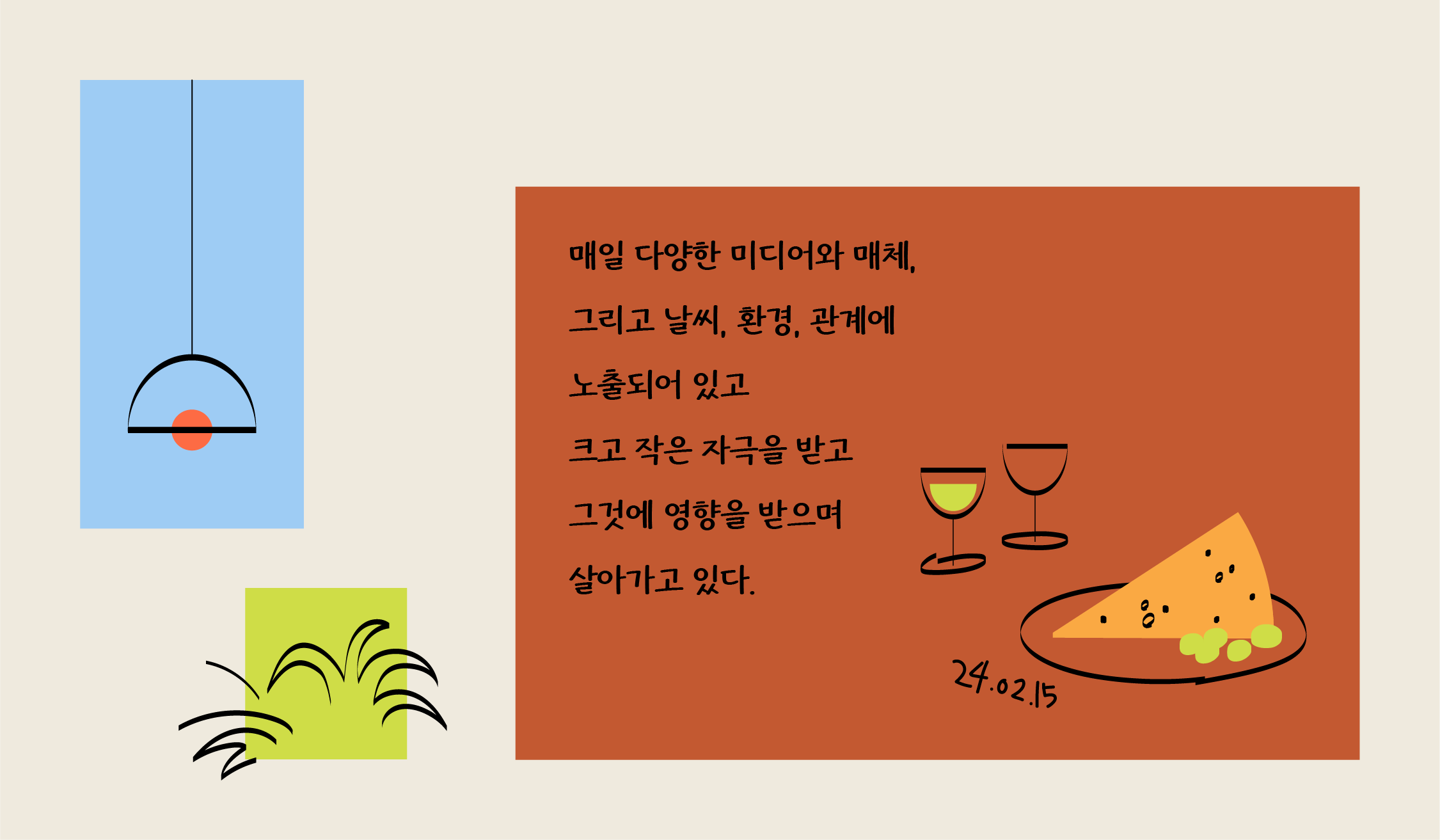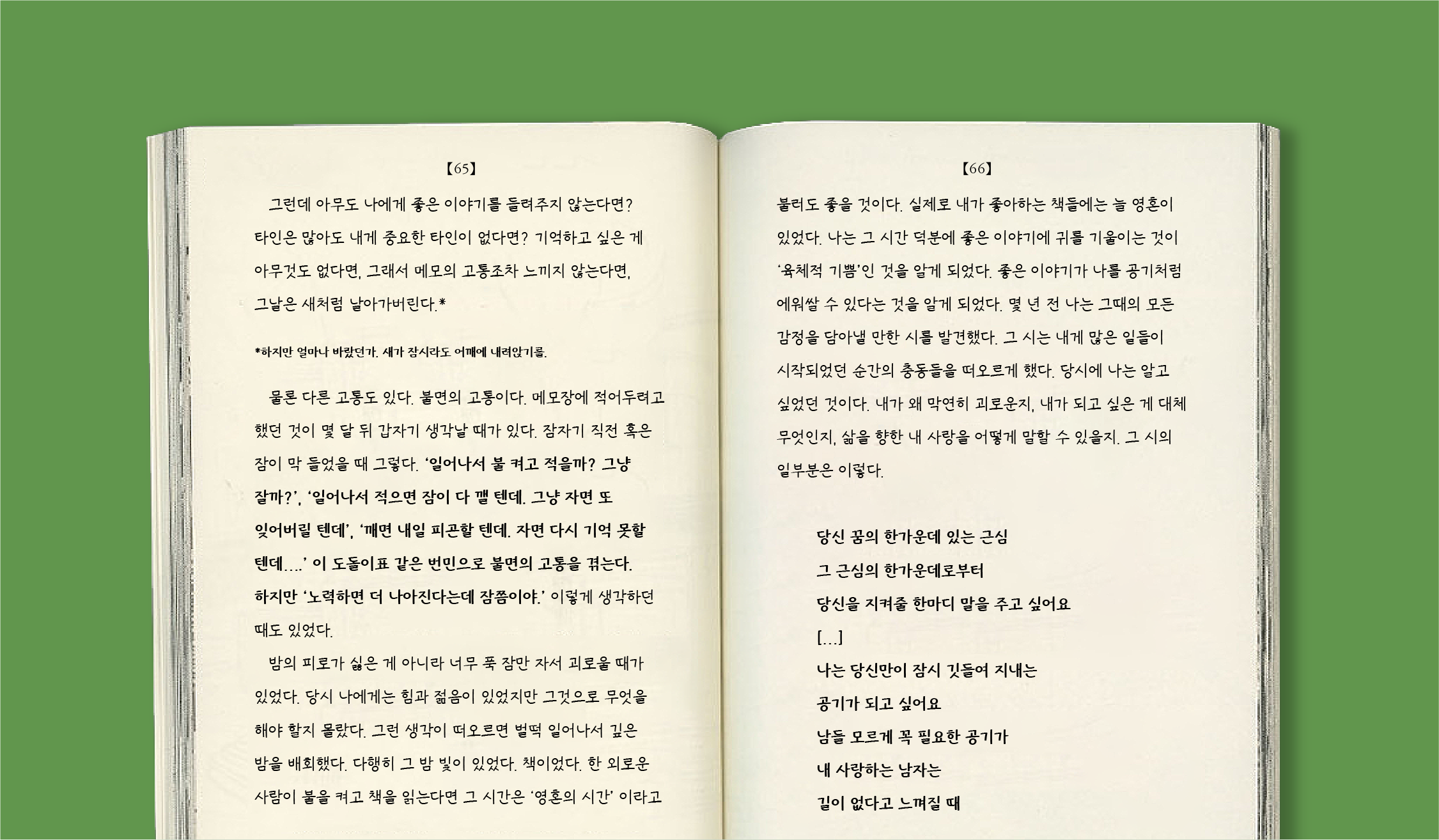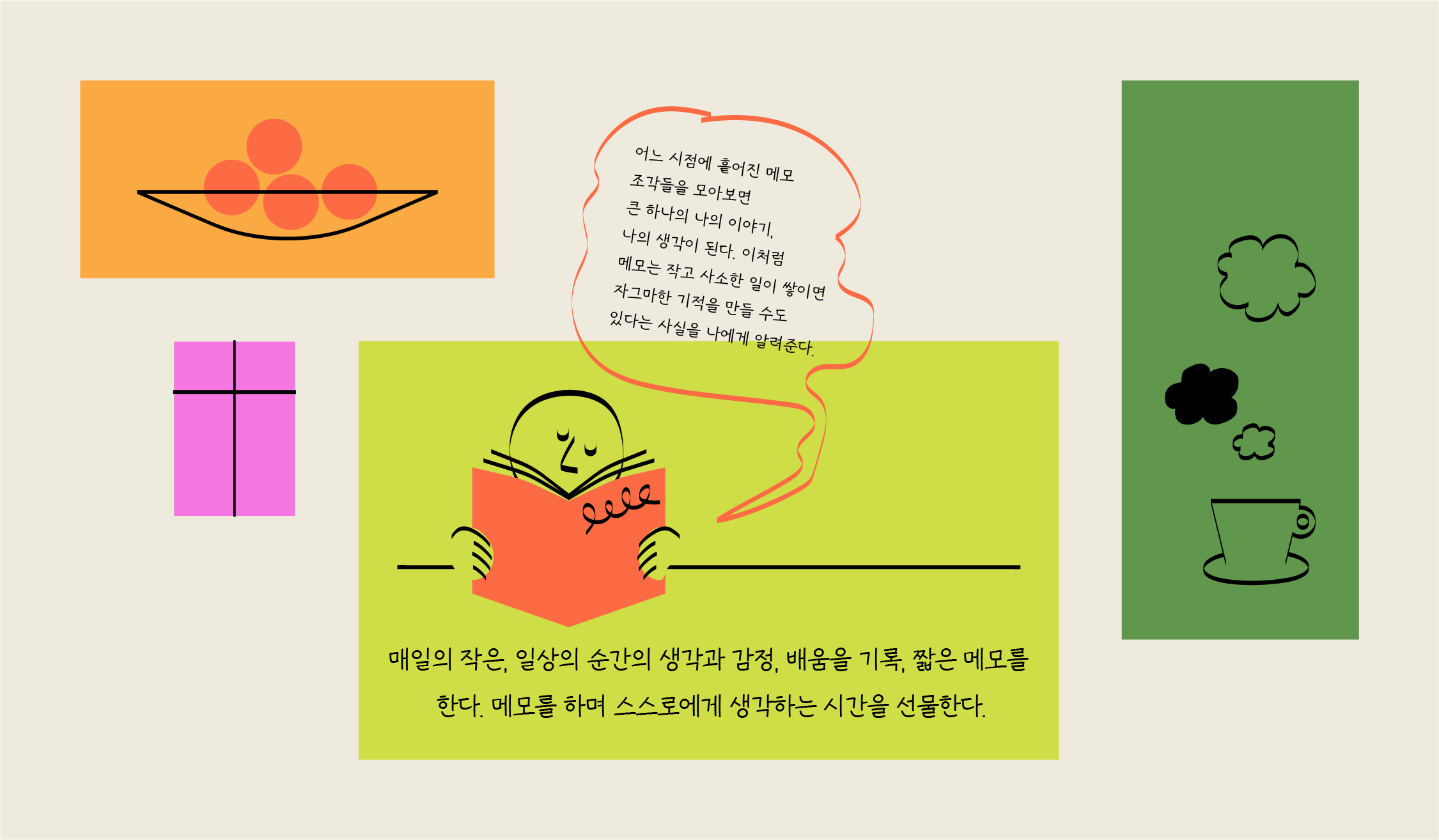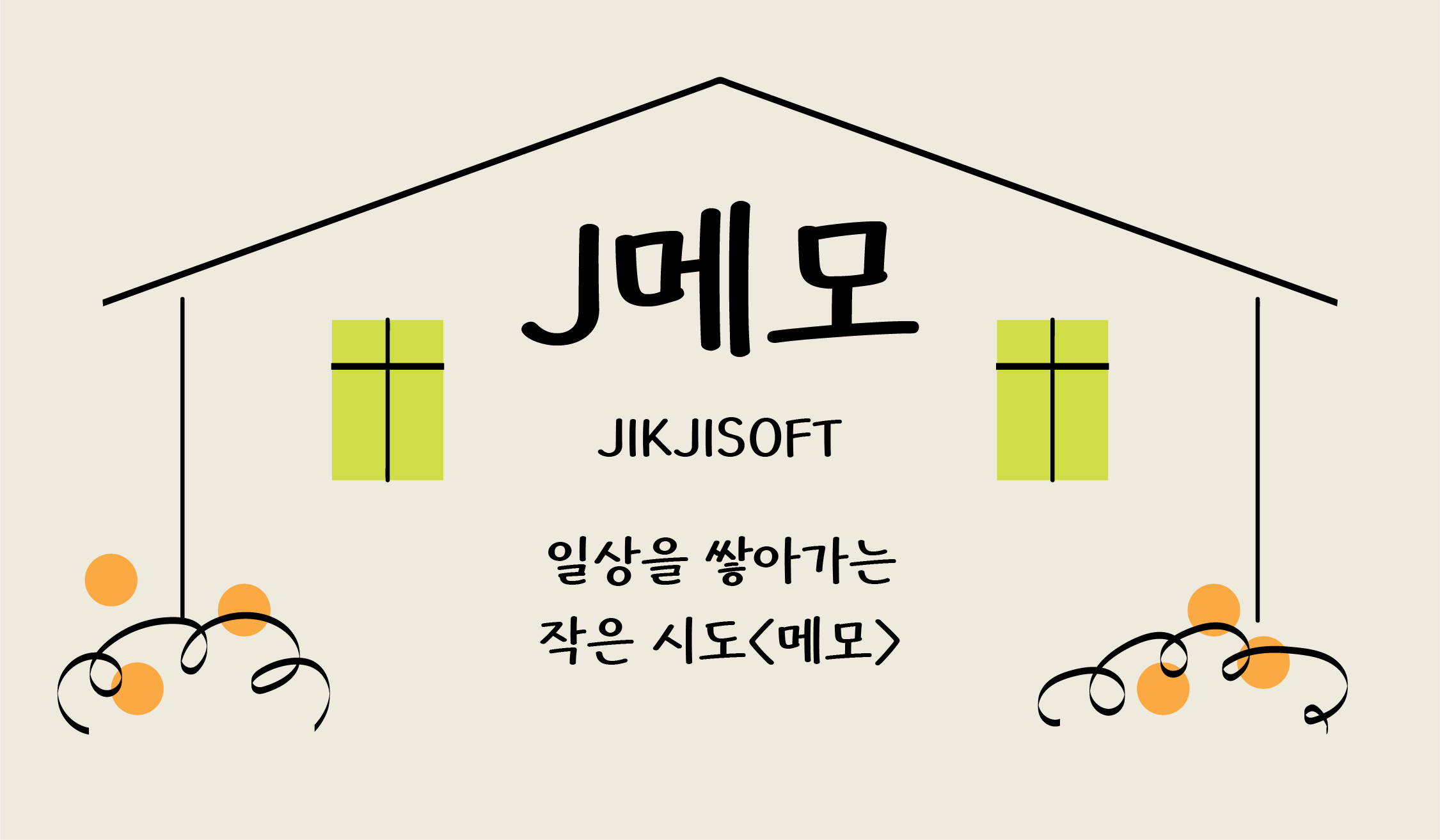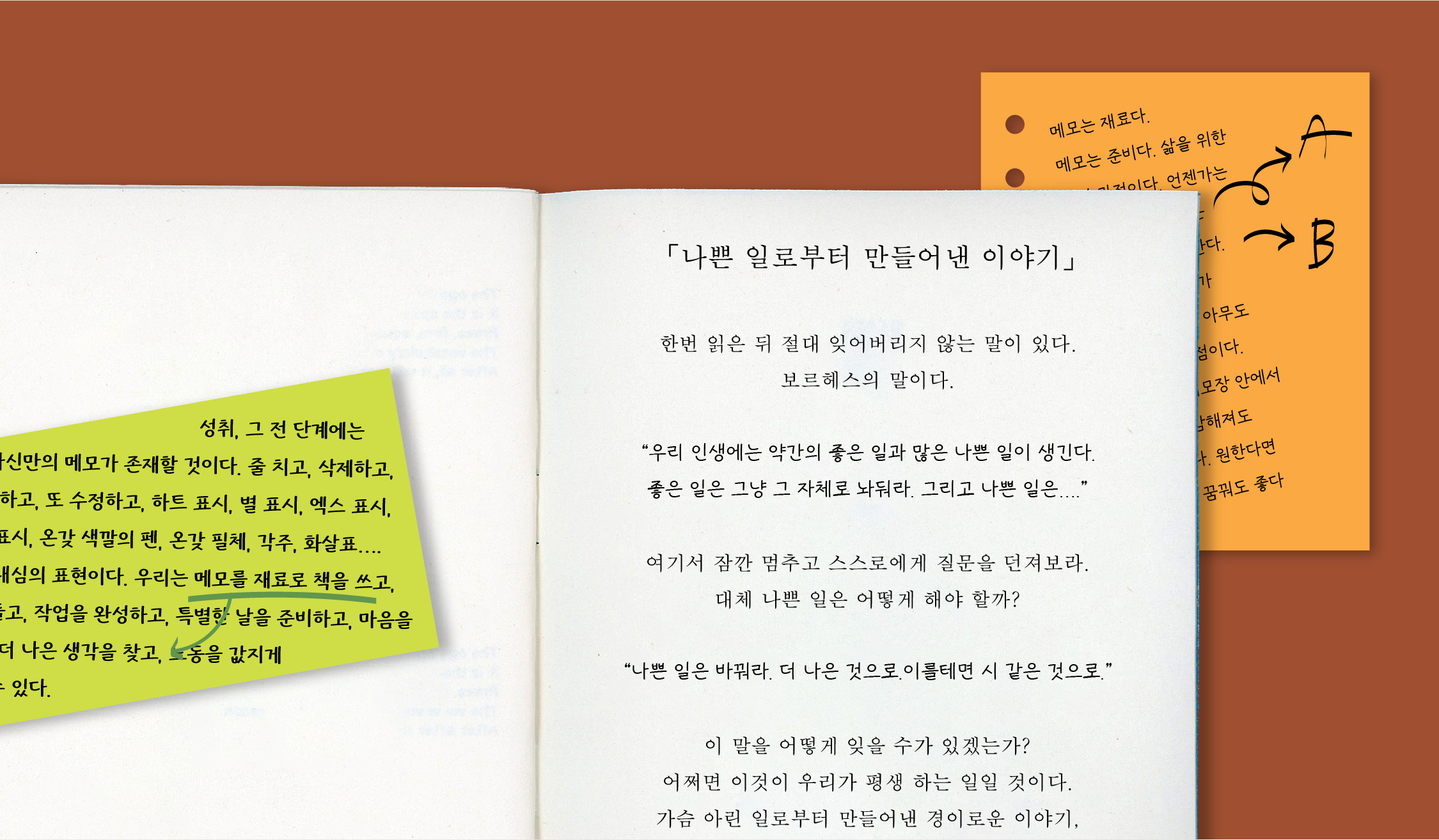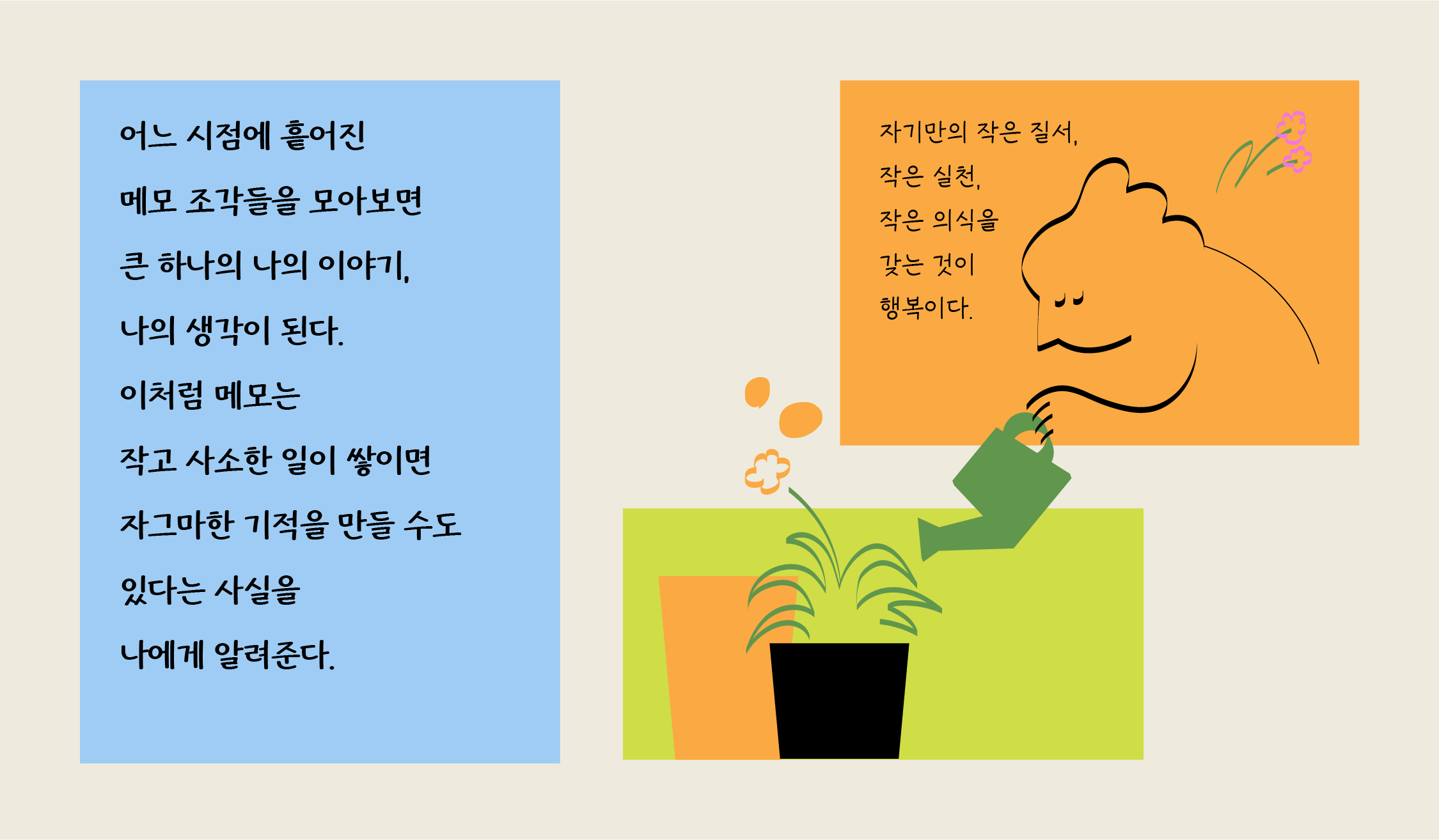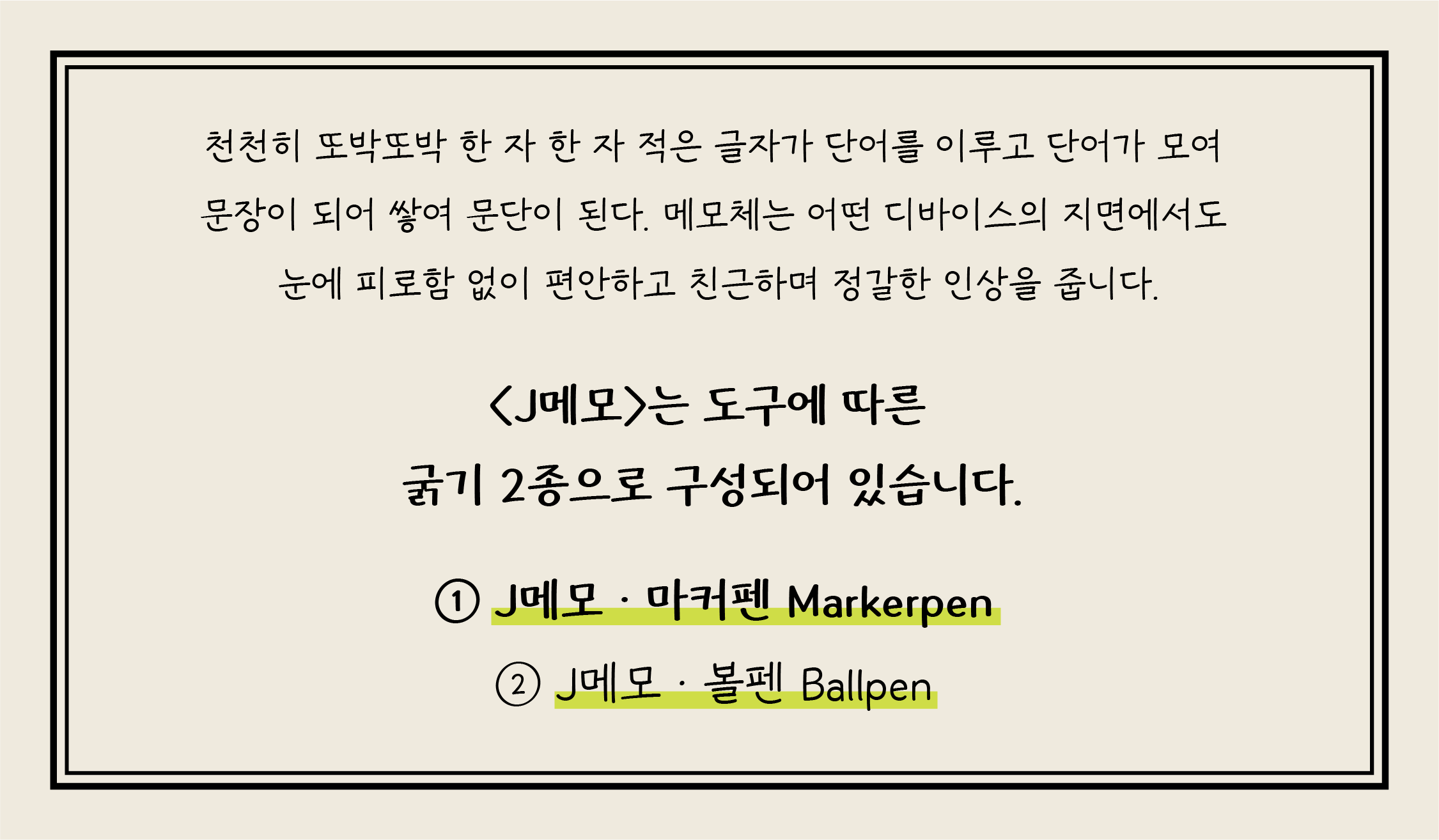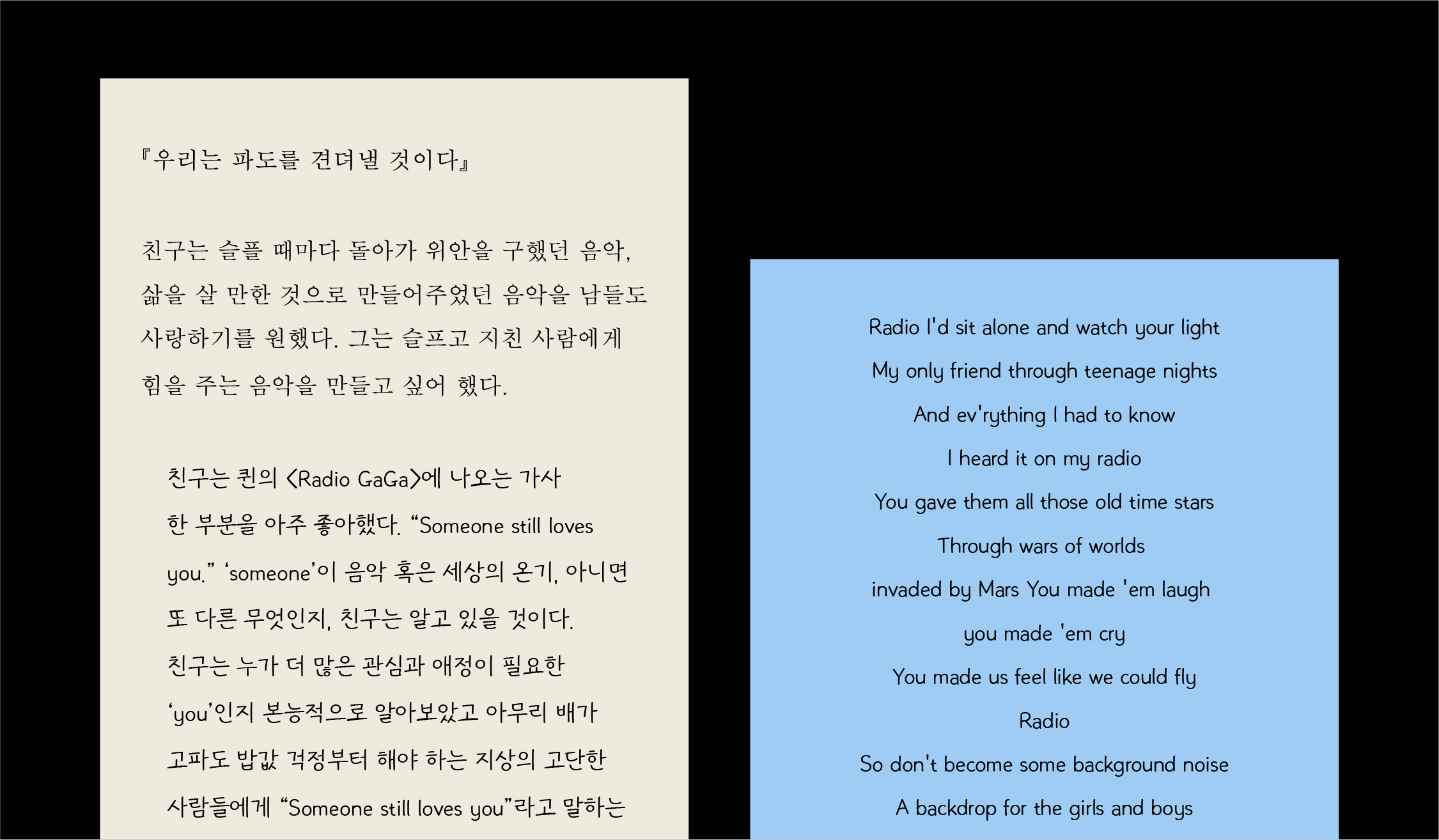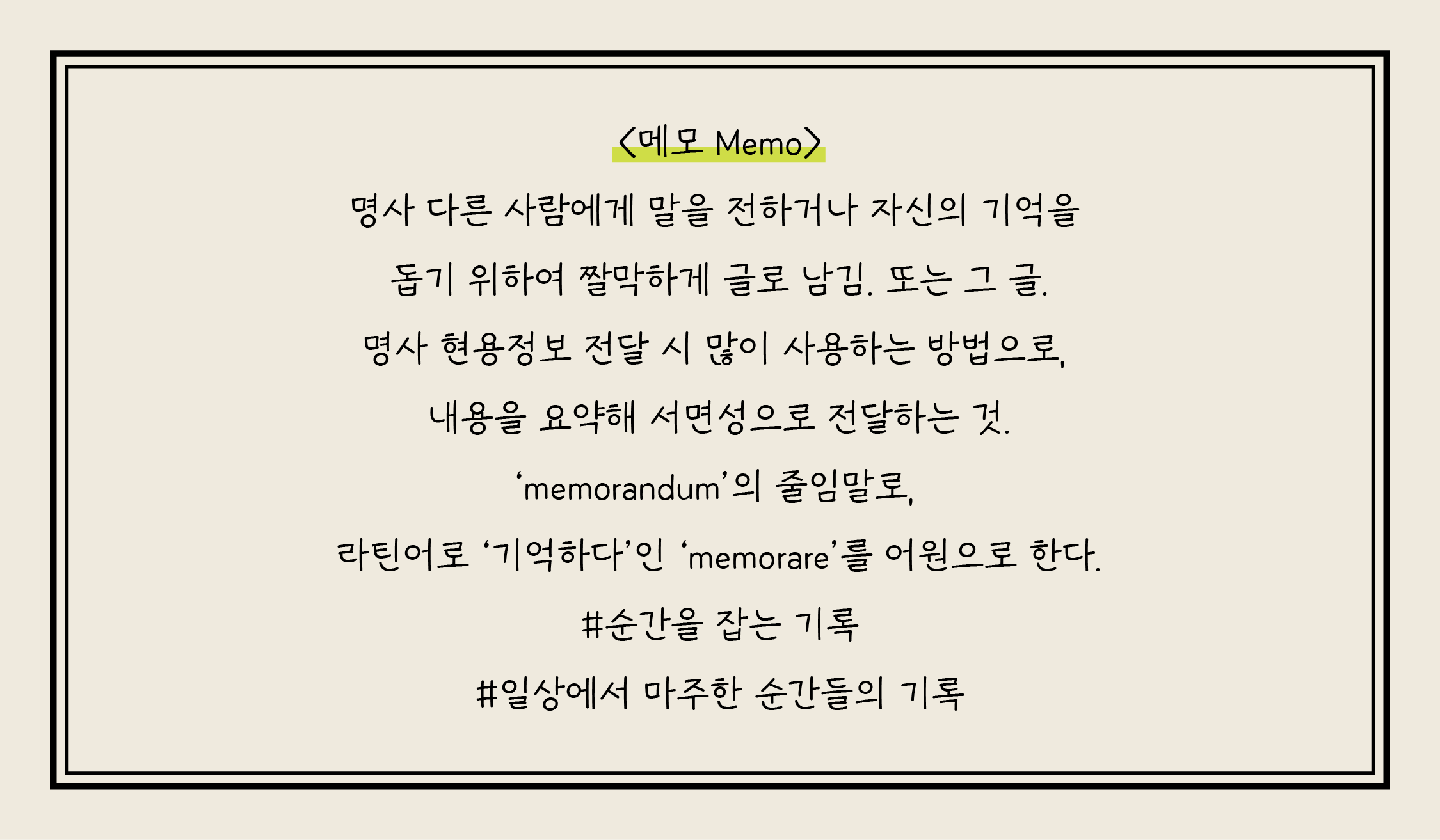
J메모
마커펜
볼펜
폰트 스펙
종수
2종
마커펜, 볼펜
패밀리 여부
폰트 패밀리
글자수
한글 2,780자
라틴 94자
특수문자 986자
디자인 연도
2024
출시일
2024.04.26
디자이너
박수진
직지손글씨
손글씨가 주는 친근함과 개성이 돋보이는 서체이다.
폰트 설명
천천히 또박또박 한 자 한 자 적은 글자가 단어를 이루고 단어가 모여 문장이 쌓여 문단이 됩니다. 매일의 사소한 메모가 쌓이면 자그마한 기적을 만들수도 있는 것이 메모라는 생각에서 시작되었습니다. <J메모>는 어떤 디바이스의 지면에서도 눈에 피로함 없이 편안하고 친근하며 정갈한 인상을 줍니다. <J메모>는 도구에 따른 굵기 2종으로 구성되어 있습니다. J메모-마커펜 / J메모-볼펜